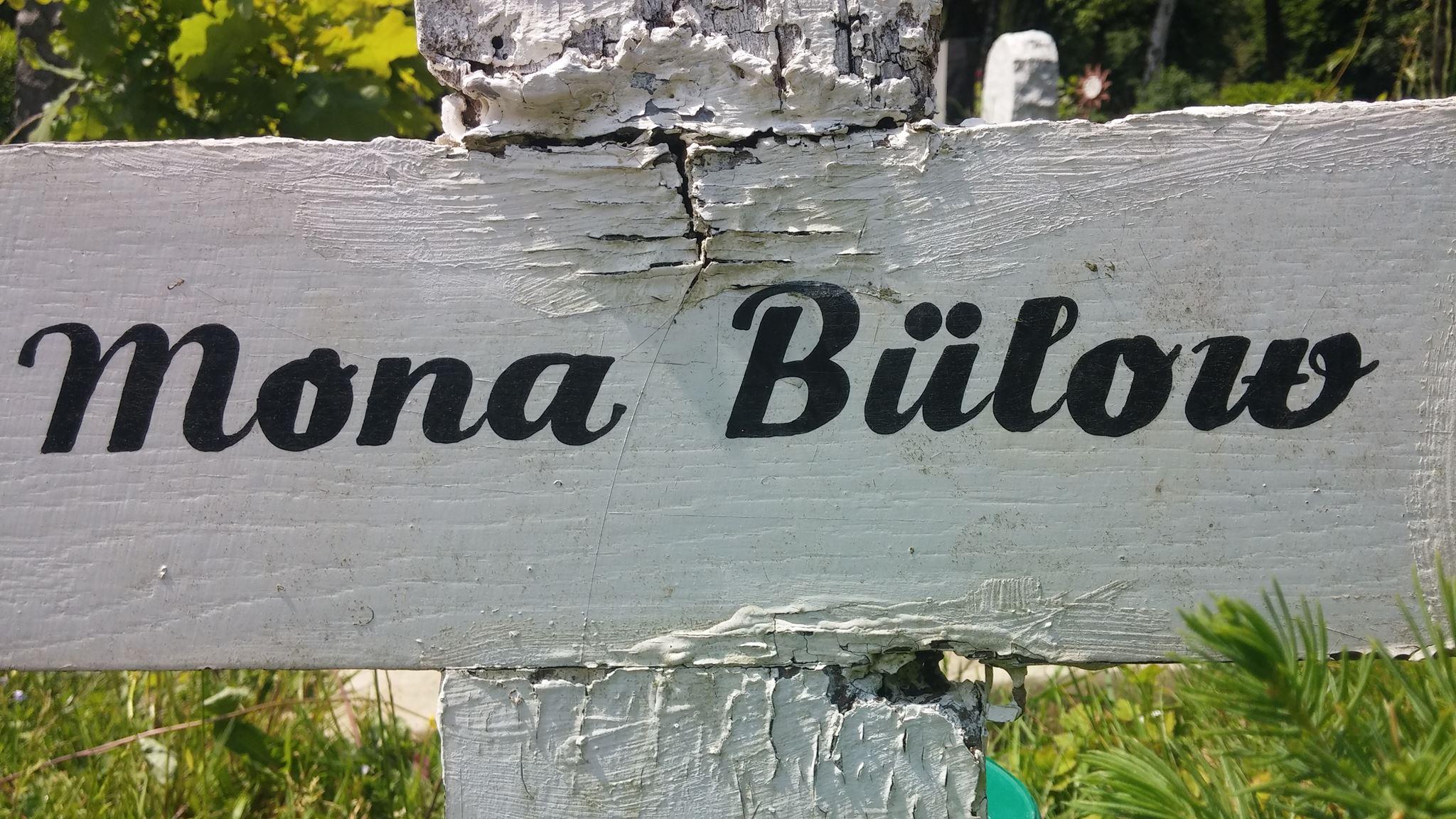
40 Jahre alte Schrift von Grabkreuz gesucht
wir möchten gerne ein neues Grabkreuz für meine Schwester machen lassen - möglichst mit der gleichen Schrift, die damals vor 40 Jahren verwendet wurde. Vielleicht weiß einer von Euch, welche Schrift das sein könnte oder kennt eine, die zumindest sehr ähnlich ist. Das wäre wirklich toll! Vielen, vielen Dank schon jetzt an alle!
Nun, das hier ist das Werk eines Schildermalers - die damals, als es noch keine Computerschriften und Letraset-Abrubbel-Buchstaben nur in den Grafiker-Bedarfs-Läden in der Großstadt gab, auch Schriftgestalter in Personalunion waren.
Ich könnte mir vorstellen dass wir hier jemanden haben, der das auch hin"schnitzeln" kann.
Sonst könnte ich mir vorstellen, auf eine entfernt ähnliche auszuweichen, vielleicht ist die ja was für dich:
Die Alternativschrift von Dir finde ich schon ziemlich gut! Welche ist das denn genau (konnte ich nicht herauslesen) und hast Du eine Idee wo ich sie dann herbekommen würde?
Oh?  Die Schrift heißt tatsächlich Prägefest, und bekommen tust du die auf der von mir verlinkten Seite. Einfach den grünen Button links unter dem Text "Fontpaket herunterladen:" klicken :-) - und die Schrift ist tatsächlich von mir.